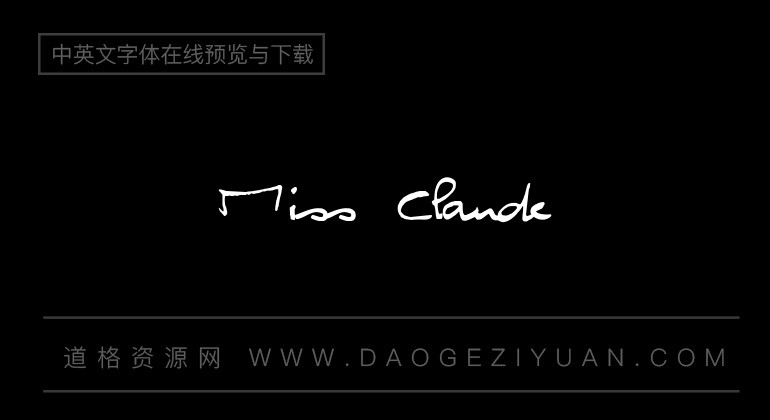
Miss Claude 是一款可爱的手写字体,由著名设计师ClaudePelletier设计。它具有细腻的线条,温柔的曲线,柔和的色调,以及细节丰富的字母,为您的设计带来温暖的感觉。它适用于海报,标志,T恤,卡片,书籍封面,网页,以及其他多种设计场景。内容介绍
Miss Claude是一款非常不错的手写艺术字体,具有很好的视觉感,适合于文化类的宣传设计、商业类品牌的广告和产品包装设计以及个性化文字排版等较多场景。